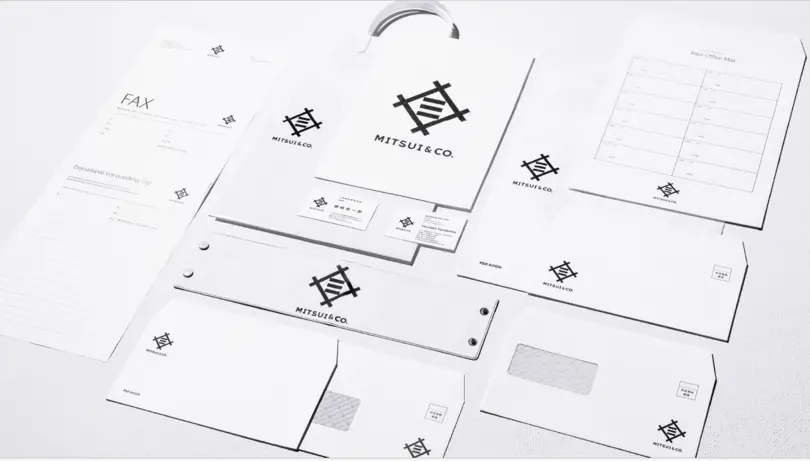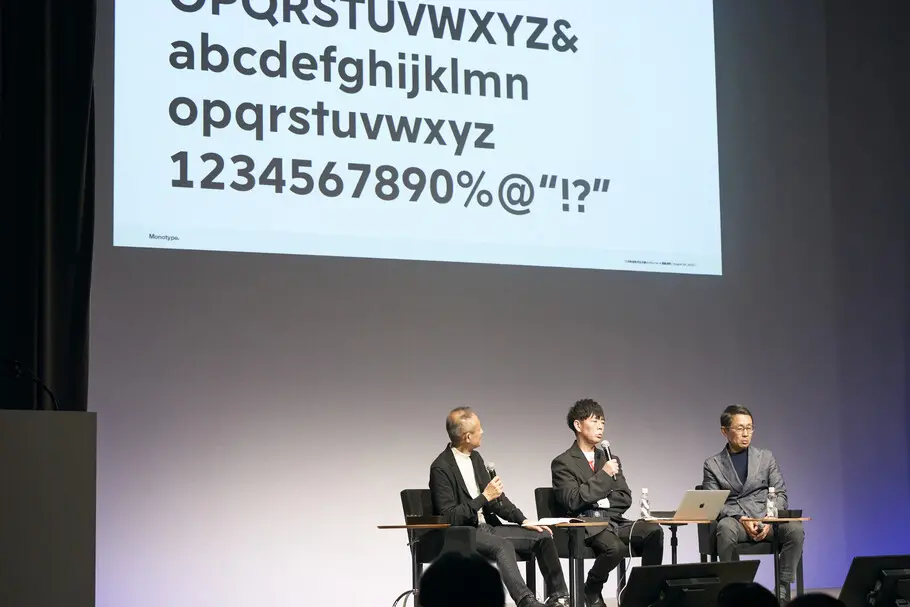
事例から学ぶ、ブランド創り「ロゴが表現する企業の姿をカスタムフォントに」
Monotype が担当したプロジェクトについて、三井物産株式会社から理事広報部長を務める古川智章氏、日本を代表するクリエイティブディレクター佐藤可士和氏と Monotype 小林章が登壇し、コーポレートブランディングのための重要なポイントについてお話しました。
セッション3つ目は、 Monotype が担当したプロジェクトについて、三井物産株式会社(以下、三井物産)から理事広報部長を務める古川智章氏、日本を代表するクリエイティブディレクター佐藤可士和氏と Monotype 小林章が登壇し、コーポレートブランディングのための重要なポイントについてお話しました。
今回、Monotypeが担当したのは世界に展開するグローバル企業である三井物産のための、欧文フォントの制作です。このプロジェクトを振り返りながら、リブランディングの進め方やフォントの役割について話しました。
三井物産は、2014年に企業理念を明確にグローバルに浸透させるため、クリエイティブディレクター佐藤可士和氏をトータル・プロデューサーとして起用し、三井物産ブランド・プロジェクトとしてブランディングを構築してきました。今回のカスタムフォントのプロジェクトもその一つです。
三井物産ブランド・プロジェクトでは、「人の三井」という言葉を重要視し、社風として長く使われてきた価値を考慮に入れ、従業員をメディアとして活用し、ブランドの理念を世に広めるための取り組みを行っています。これは、三井物産が多言語展開するグローバル企業として、国や市場の違いを超え、統一されたブランドの価値を世界中に発信するという目標を体現したものです。
本セッションでは、本プロジェクトの発足に至るまでの考えや、経緯、ブランディングとの関わり方などを解説。さらに、三井物産、佐藤氏とMonotypeの3社間でどのように欧文書体の制作が進められたのか具体的な例を交えデザインに込めた思いを議論しました。
佐藤氏は以下のように話しました。ブランディングとは、その企業やブランドの世界観を発信し、コントロールすることであり、社会の中でどのような存在として創り上げていくかという活動だと思います。情報を発信する際は、必ず文字情報が入るため、ロゴとの統一感やフォントが与える印象を考慮することは、ブランディングにとって不可欠であると思います。
カスタムフォントのプロジェクトは、三井物産のブランド・プロジェクトの一環ですが、このフォントは長期に渡り、使われ続けます。世界中でビジネスを展開する上で様々な状況に合わせたコミュニケーションが必要な企業にとって、フォントが担う役割はとても大きいということが分かります。